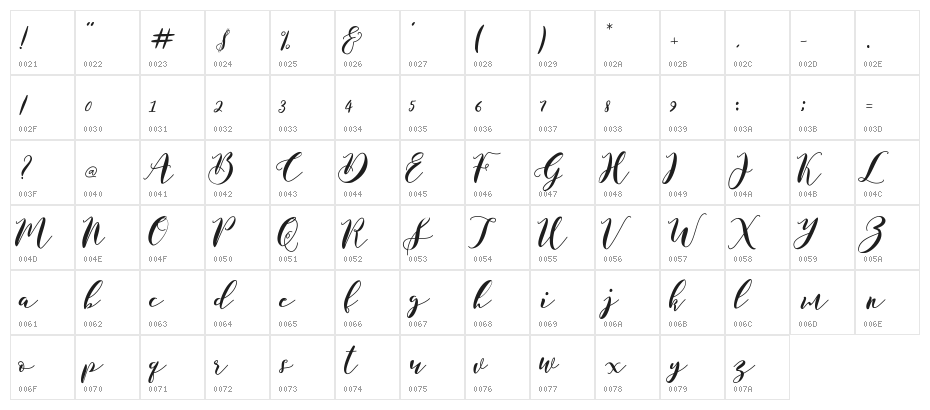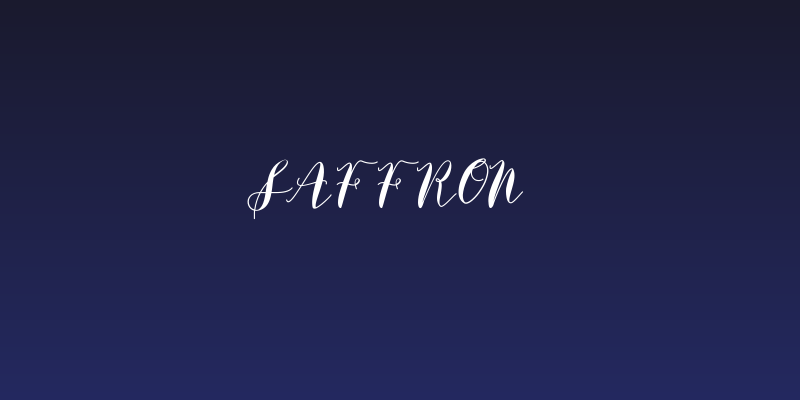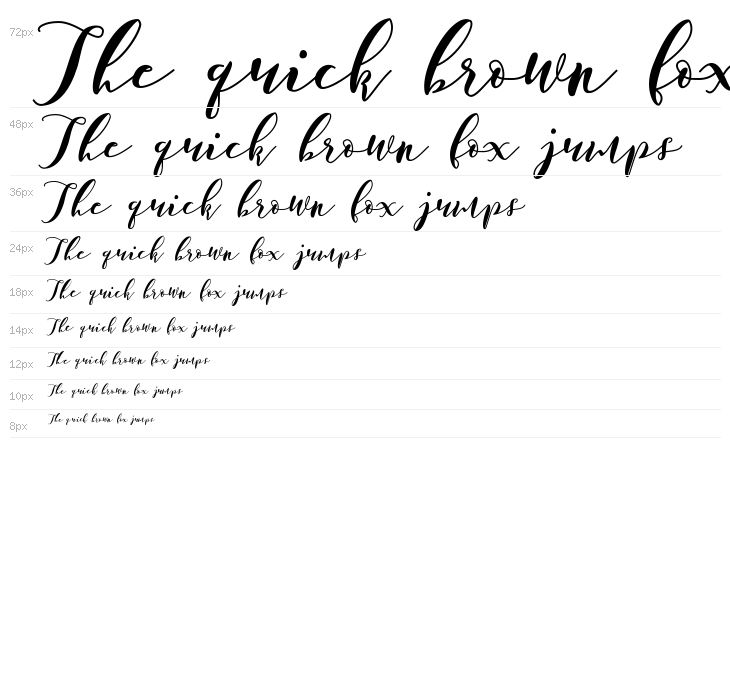
Saffron Font
✎ Script
| Anwendungsfall | Logos, Invitations, Branding |
| Vorgeschlagene Projekte | Ideal for wedding invitations, branding, greeting cards, and elegant packaging designs. |